七夕节快乐!为了让这个浪漫的节日更加精彩,我们特别为大家准备了一场字体展示盛宴。让我们一起在文字的世界中感受浓浓的爱意吧!
萌萌哒可爱字体
用这款可爱的字体,将你对TA的爱意表达得淋漓尽致。每一个字母都带着甜蜜的笑容,仿佛在告诉世界,你们的爱情是多么美好。快来试试吧,让文字也变得可爱起来!
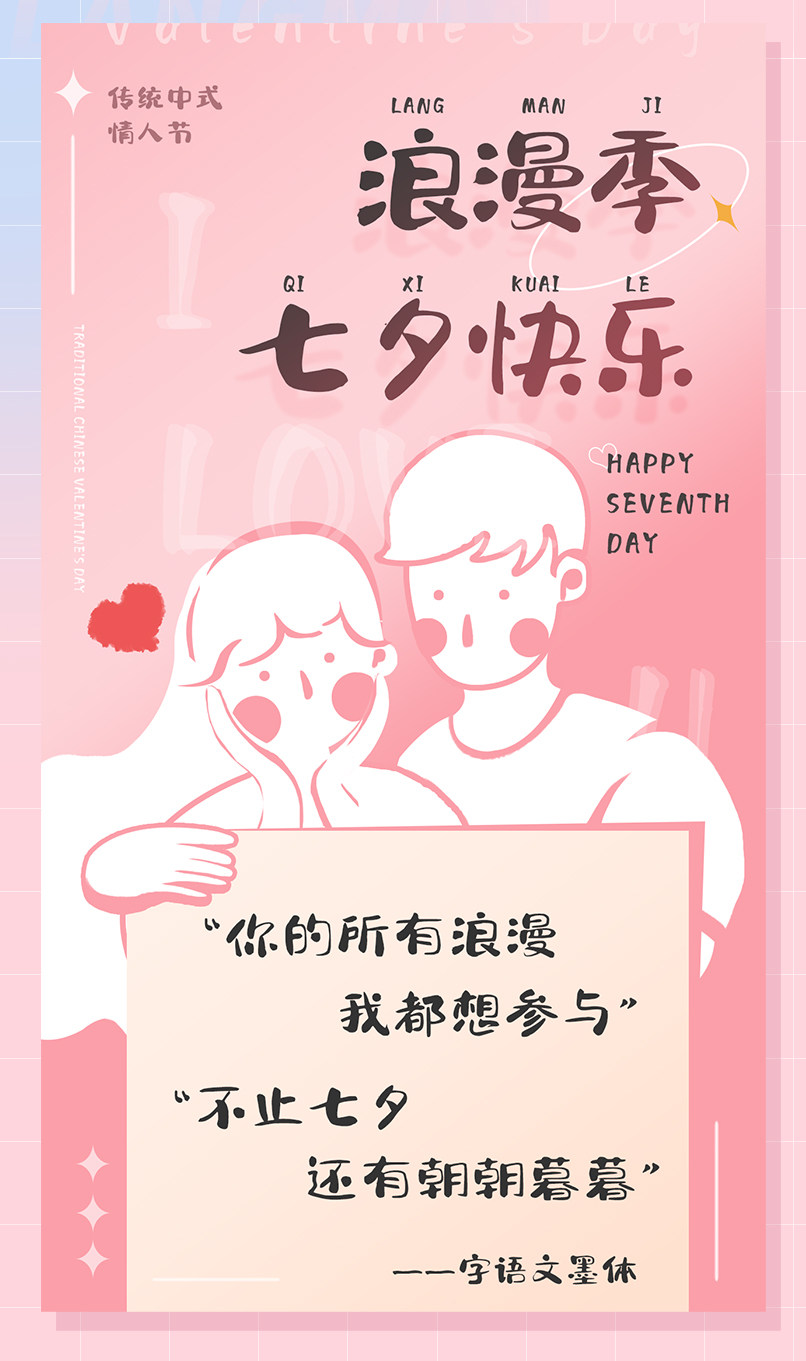
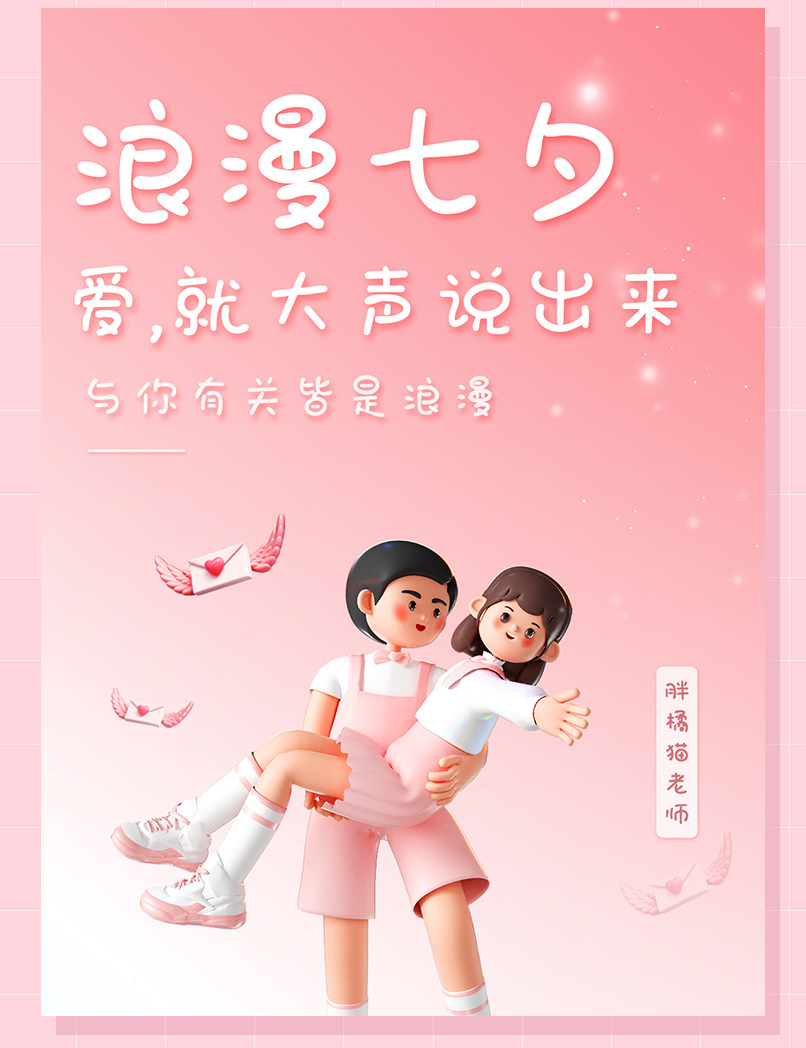
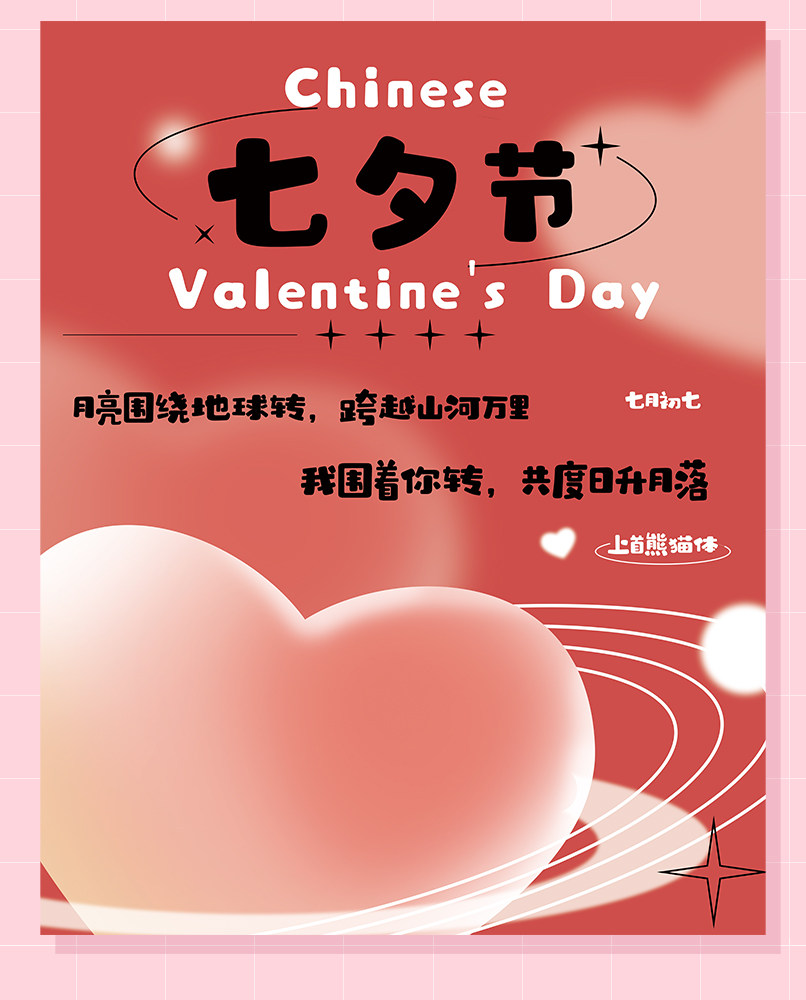
飘逸浪漫手写字体
七夕夜,写下你们的爱情宣言,让字体的笔画跳跃出动人的旋律。这款飘逸浪漫的手写字体,仿佛是从天堂中降临,让每一个字母都沐浴在爱的氛围中。在这个特殊的夜晚,用它为你们的爱情增添一抹浪漫吧!
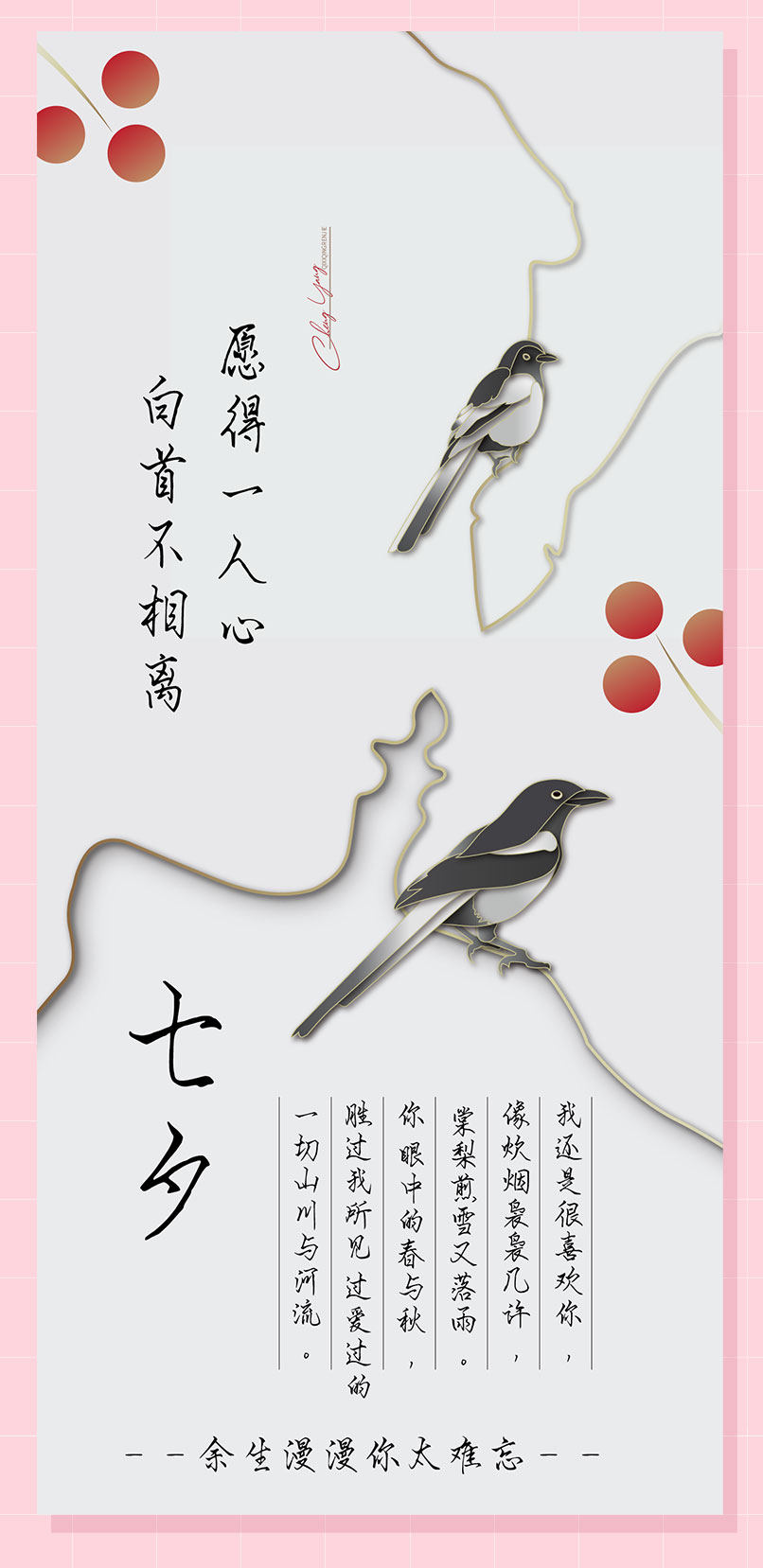
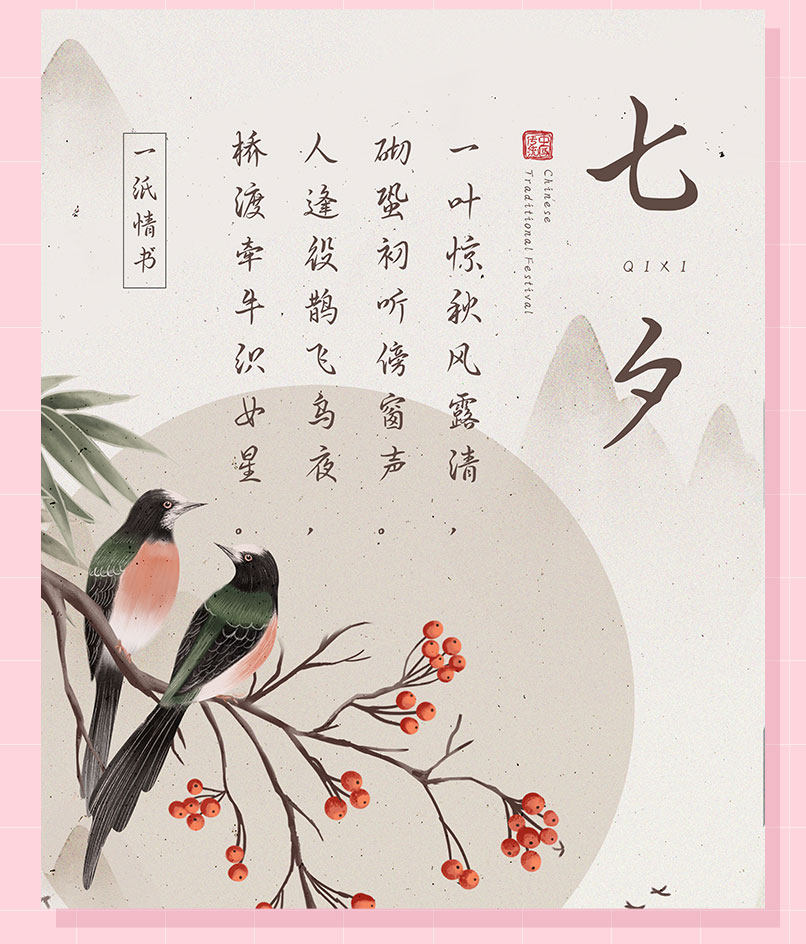
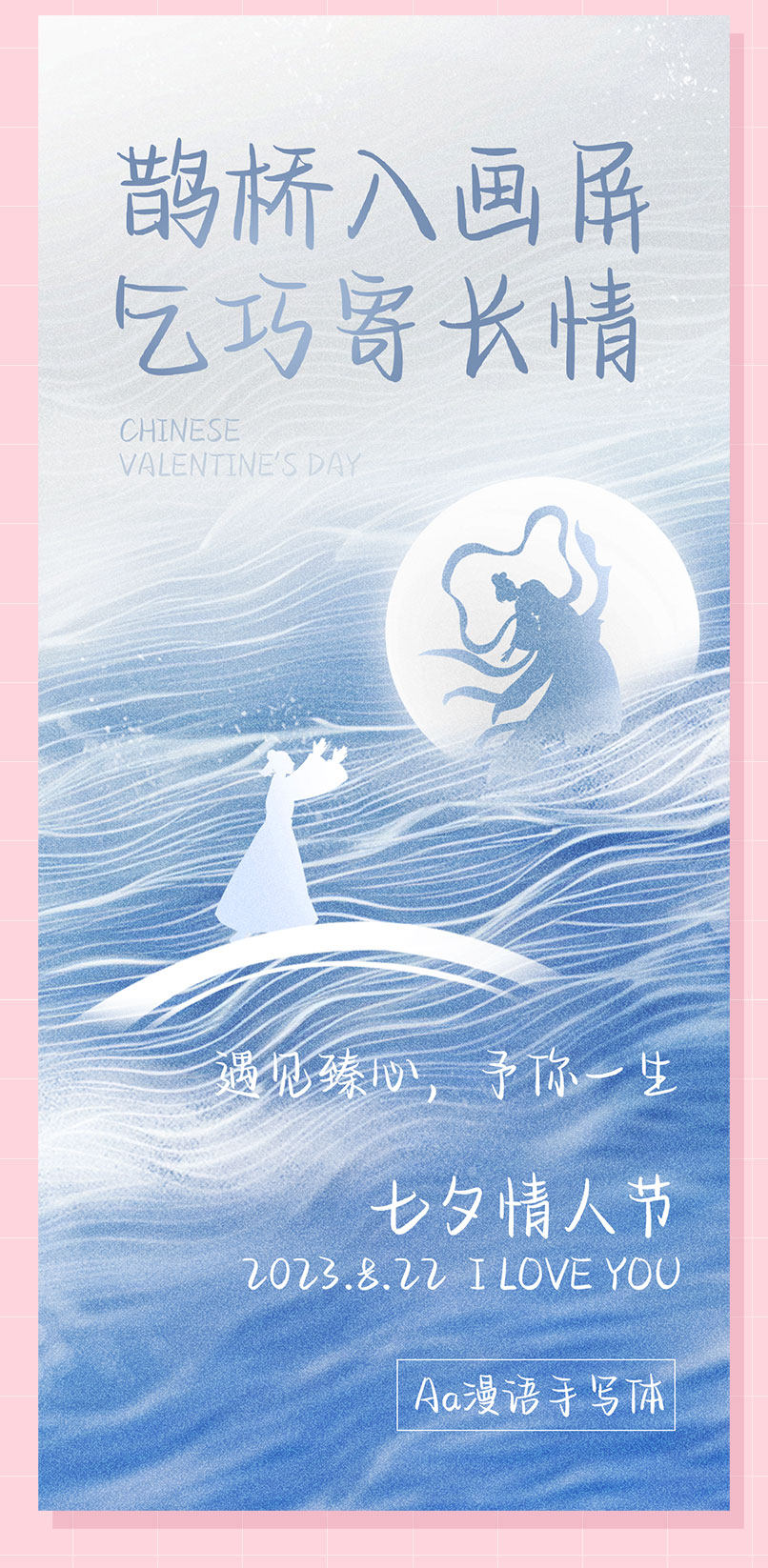
经典古风字体
穿越时空,感受古代诗词的韵味。这款经典古风字体,犹如悠扬的古琴声,将你们的爱情故事诠释得淋漓尽致。用它书写一段永恒的誓言,让爱在岁月的长河中流传下去。
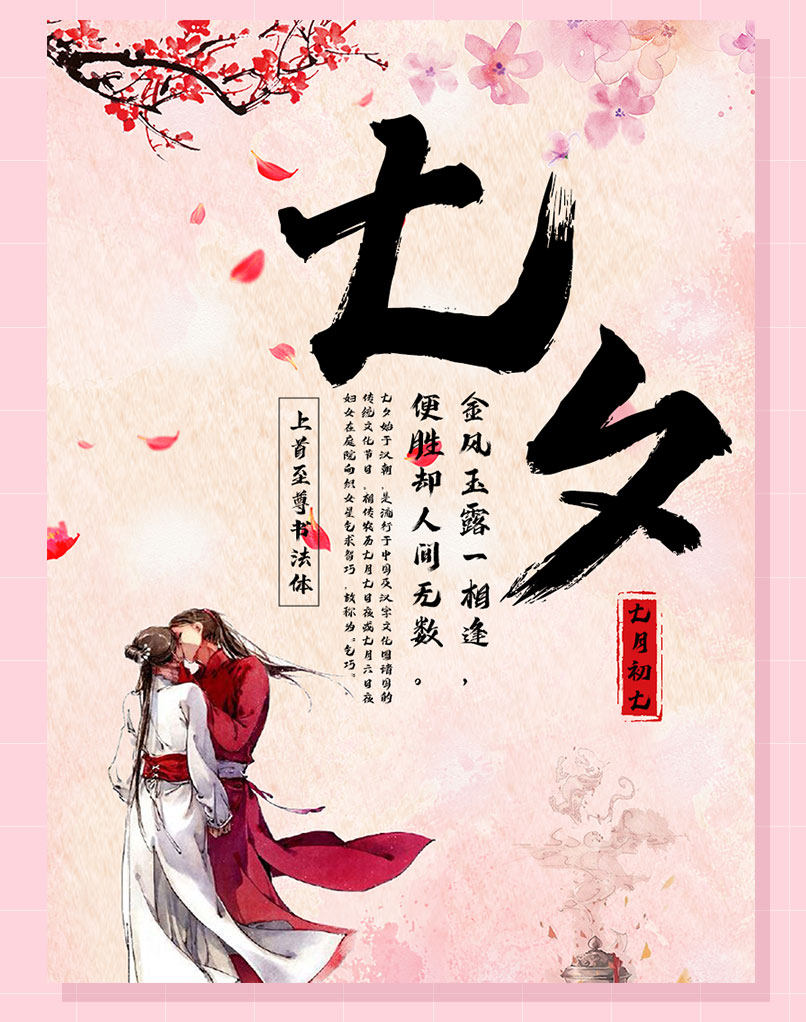
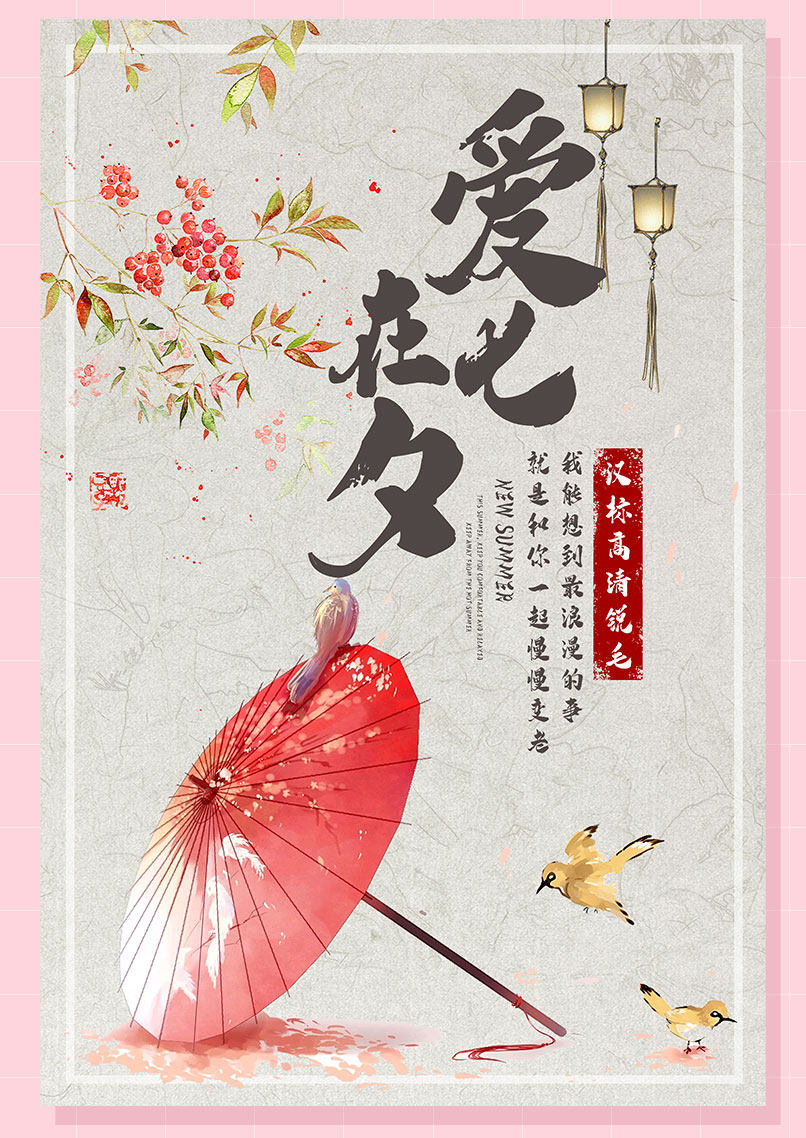
无论你是想向心爱的人表白,还是为自己增添一份浪漫的情怀,这里都有各种各样的字体供你选择。让文字成为你表达爱意的媒介,让七夕节的甜蜜在字体间绽放。